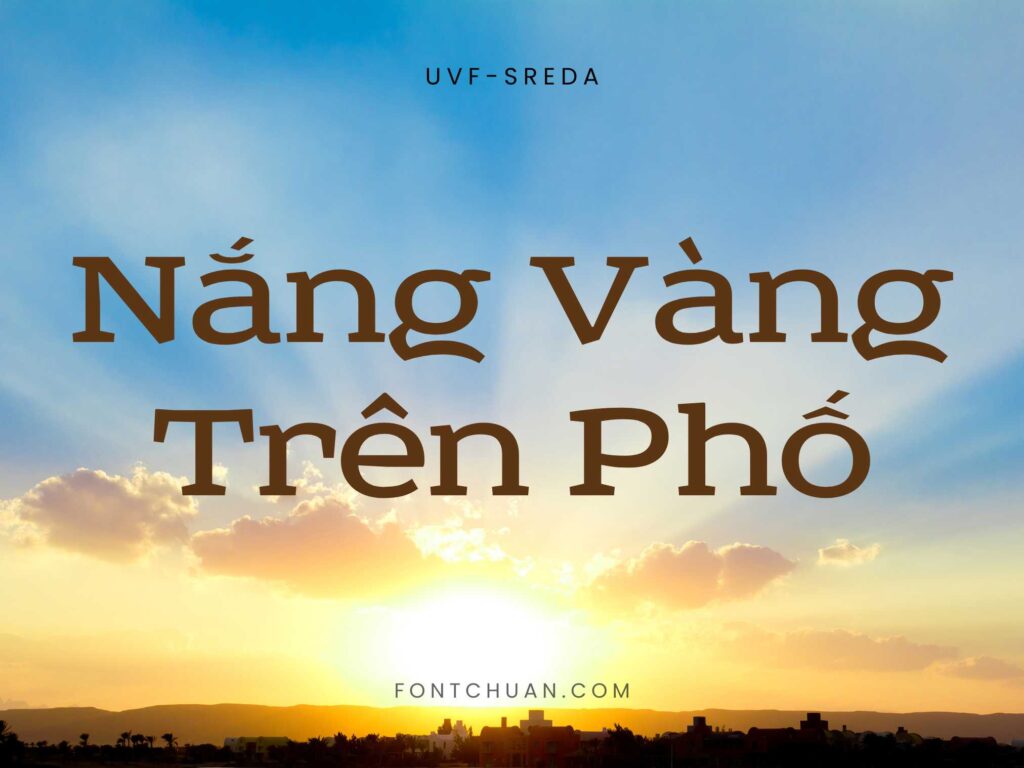
Font UVF Sreda Việt Hóa
Sreda là một phông chữ được thiết kế bởi Glenjan, bao gồm 665 ký tự, mang lại sự đa dạng và linh hoạt cho các dự án thiết kế. Phông chữ này đã được Việt hóa, hỗ trợ đầy đủ các ký tự tiếng Việt, giúp người dùng tại Việt Nam dễ dàng sử dụng trong các dự án sáng tạo của mình.
Với thiết kế độc đáo và nghệ thuật, Sreda phù hợp cho các ứng dụng như thiệp mời, logo thương hiệu cao cấp, bìa sách hoặc các ấn phẩm đặc biệt, nơi cần tạo ra sự ấn tượng mạnh mẽ về thị giác và cảm xúc. Trong lĩnh vực sự kiện, phông chữ này có thể được sử dụng trong các dịp như lễ hội, lễ cưới và các sự kiện văn hóa. Ngoài ra, Sreda cũng thích hợp cho các ngành nghề như thiết kế đồ họa, nghệ thuật trang trí và xuất bản.
Việt hóa: Beautype Studio
Tác giả: Justin Callaghan
Tác giả: Puguh Sahirul, Semarang, Alexatype